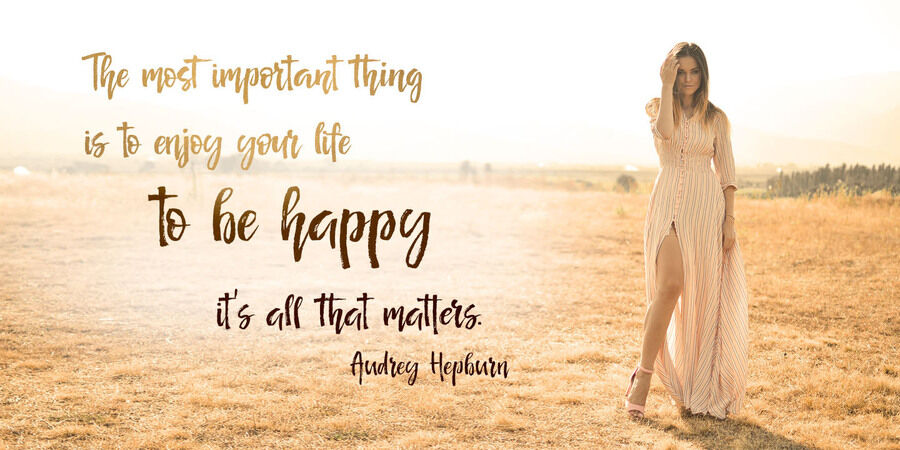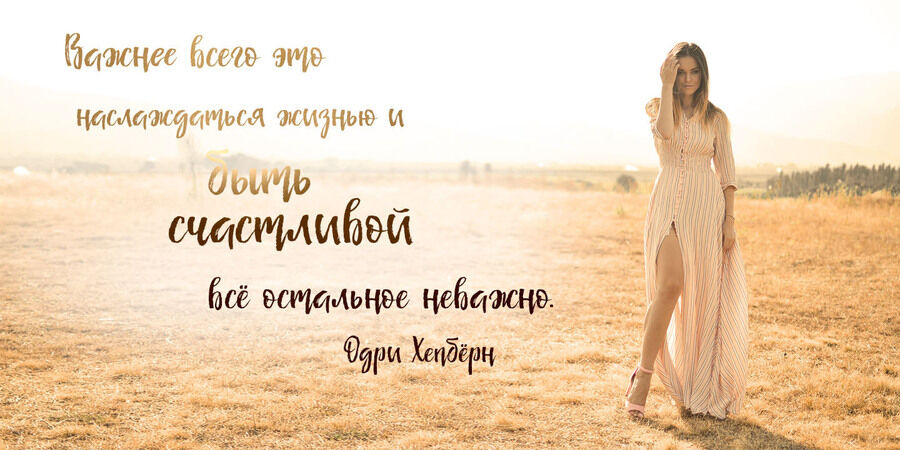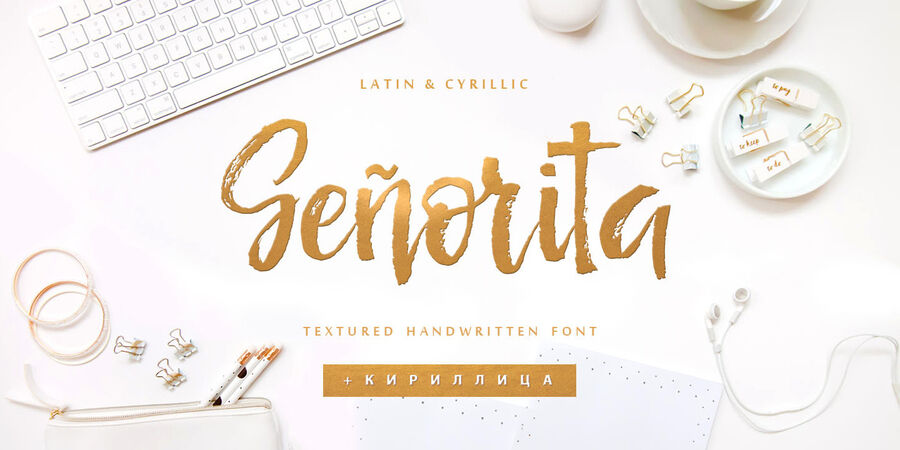
Рукописный текстурный шрифт Señorita (Сеньорита) был написан сухой кистью и отлично подойдет для дизайна брендов, плакатов, одежды, логотипов, заголовков сайтов, дизайна одежды, дизайна свадебных открыток и многого другого. Этот каллиграфический шрифт содержит полный набор прописных букв и 2 полных набора строчных букв и 43 лигатуры. Используйте чередующиеся строчные и двухбуквенные лигатуры, чтобы придать своим творениям идеальный вид ручного письма. Кириллическая часть шрифта содержит полный набор заглавных и строчных букв а также 17 лигатур, придающих реалистичный стиль вашей типографике. Многоязычная поддержка 32 языков на латинице и кириллице. Поддержка кириллицы в русском, белорусском, украинском, болгарском и казахском языках. Шрифт разработала Ирина Двилюк в 2021 году.
Асоціації з сімейством шрифтів Senorita CyrillicОсобистість і характер гарнітури:
новорічний, активний, яскравий, ритмічний, енергійний, святковий, музичний, художній, мрійливий, радісний, майстерний, якісний, виразний, помітний, модний, емоційний, чуттєвий, поетичний, оригінальний, характерний, самобутній, весняний, літній, артистичний, танцюючий, цікавий, красивий, темпераментний, натхненний, лихий, неохайний, швидкий, динамічний, вільний, колоритний, живий, крафтовий, доброзичливий, рукотворний, зелений, екологічний, природний, творчий, експресивний, артізанальний, натуральний, моторний, рослинний, розмашистий, жіночний, ошатний, романтичний, щасливий, симпатичний, дівчачий, смачний, ручний, затишний, довірчий, теплий, рухливий, ламповий, апетитний, привітний, свіжий, бадьорий, квітковий, приємний, неформальний, здоровий, ефектний, естетичний, пристрасний, сексуальний
мода, танець, музика, десерт, кафе, свято, інтер'єр, квіти, шоколад, реклама, виставка, одяг, перукарня, хенд мейд, сад, клумба, щоденник, Новий рік, ресторан, цукерки, театр, татуювання, тату, подарунки, поезія, кохання, вино, літо, весна, сукня, екологія, природа, Хюґе, дерево, Інстаграм, графіка, ілюстрація, пейзаж, акварель, романтика, селфі, море, краса, бутік, їжа, відпочинок, анімація, мультфільм, мистецтво, розваги, ранок, світанок Гарнітура має ознаки стилів: